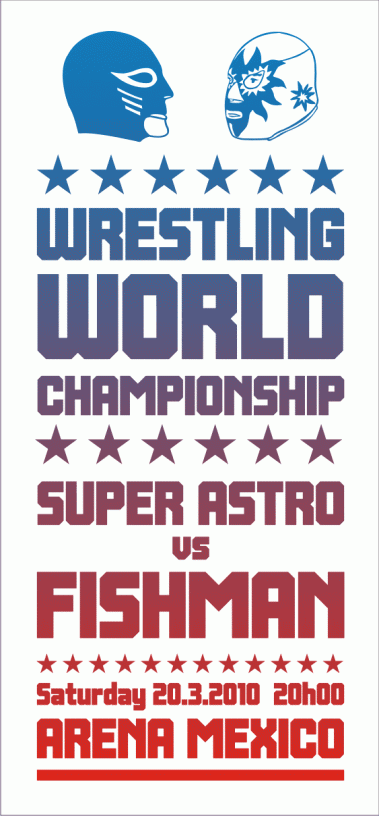
Ring
Ring está inspirada en la tipografía popular mexicana de carteles de lucha libre.
This FontStruct was inspired by wrestling typographic posters in Mexico.
The very strong design works well in the sample.
very authentic looking. nice job.